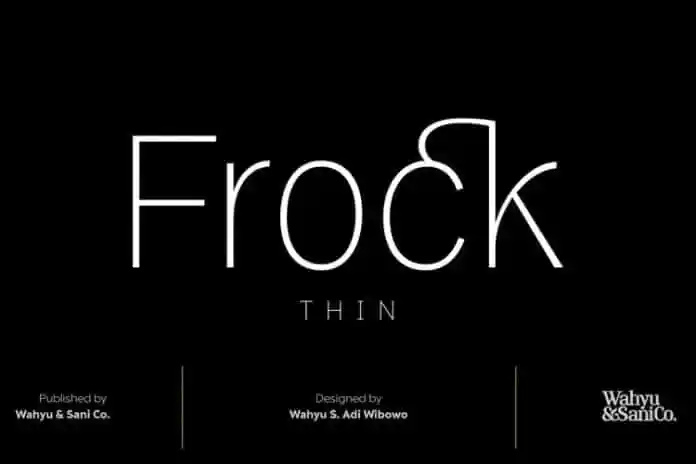
Frock Sans Serif Font – Download Grátis
A Frock Sans Serif é uma fonte que se inspira nas formas geométricas modernas, com linhas retas fortes e uma aparência leve e elegante. Desenhada por 99designs, essa fonte sans serif oferece um uso amplo para textos em papel ou tela. Uma característica interessante é a sua forma de contornos que se assemelha a um ovo inclinado, com contraste médio e uma atmosfera não tão formais inspirada nos famosos tipofaces American Gothic. A Frock Sans Serif é ideal para uso em logotipos, publicações de mídia exibição ou até mesmo panfletos e outdoors. Seu estilo elegante e moderno combina bem com qualquer projeto que busque uma fonte sem serif que seja versátil o suficiente para se adaptar a diversos usos. Não apenas isso, mas ela também oferece alternativas de estilos italico fluídos e verdadeiramente itálico, tornando-a um recurso valioso tanto para textos tradicionais quanto para designs gráficos mais elaborados.